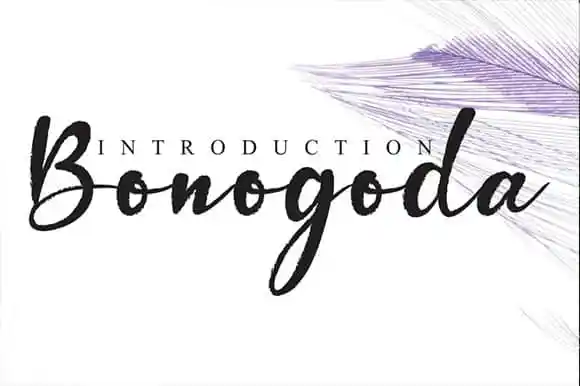
Bonogoda Brush Font – Download Grátis
A Bonogoda Brush Font é uma criação única para quem busca letras com um toque artístico e elegante. Seu design moderno e fluido é perfeito para estilos de projetos que valorizam a autenticidade, como wall displays, identidades visuais de eventos ou marcas sociais. Perfeita para personalizar embalagens, cartões de visita, logotipos de produtos e até mesmo como gráficos de foto. Com seu traço fluido e natural, esta fonte de estilo brush é o elemento ideal para dar um toque especial a qualquer projeto que busque uma aparição de autoria única. Ela está disponível em várias opções de tamanho, garantindo flexibilidade para criar designs inovadores que se encaixam perfeitamente com seu estilo e personalidade. A Bonogoda Brush Font é uma escolha inteligente para os criativos e designadores que buscam agregar um toque diferente a seus projetos digitais.